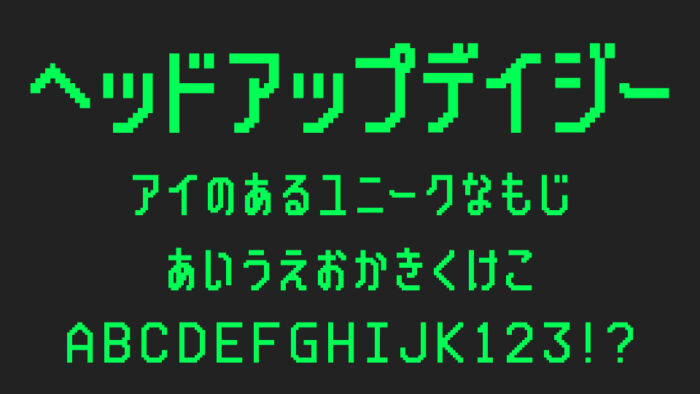
ヘッドアップデイジーフォント(x14y24pxHeadUpDaisy)は、HUD風に作られているSF感・デジタル感を感じるドットフォントです。
デジタルっぽいのに、どこか親しみやすい雰囲気を感じるフォントです。HUD風に作られているので、車やロボットなどのジャンルはもちろん、ゲームのUIやドット絵テイストのデザインにぴったりなフォントです。
ヘッドアップデイジー
収録文字は、ひらがな・カタカナ・アルファベット・数字・記号が収録されています。
ひらがな○
カタカナ○
漢字×
ヘッドアップデイジー